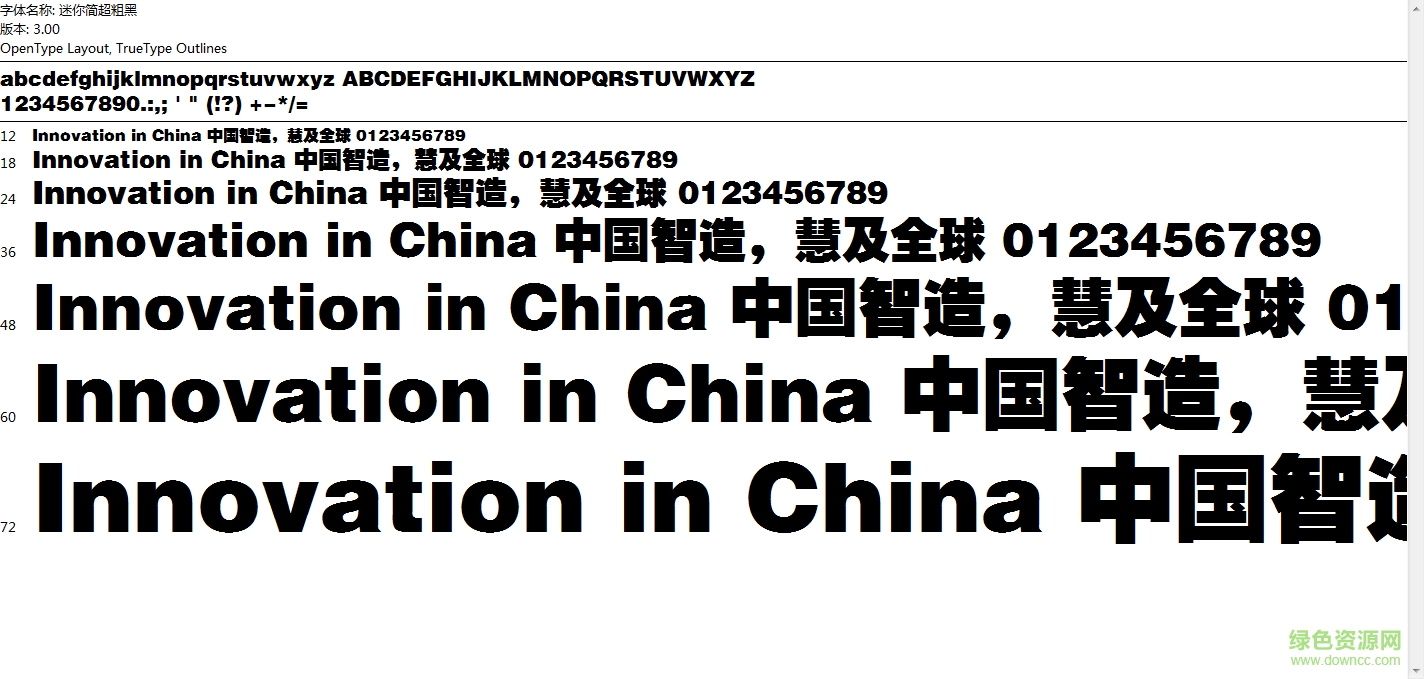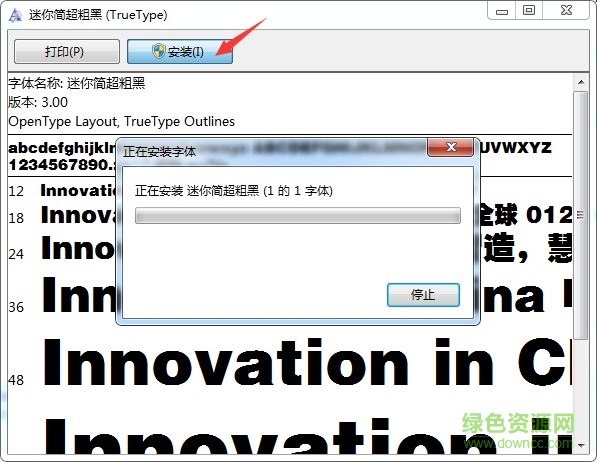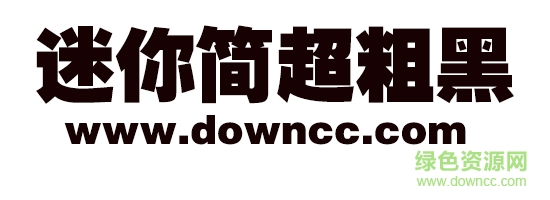
迷你簡超粗黑是迷你字體的一款粗體字體,字型整體形象渾厚有力、厚重健實,特色是比較顯目,迷你簡超粗黑體支持英文、中文、數(shù)字三種文字轉(zhuǎn)換功能,喜歡的朋友歡迎來綠色資源網(wǎng)下載!
迷你簡超粗黑體字體整體形象渾厚有力、厚重健實,特色是比較顯目,支持英文、中文、數(shù)字三種文字轉(zhuǎn)換功能。